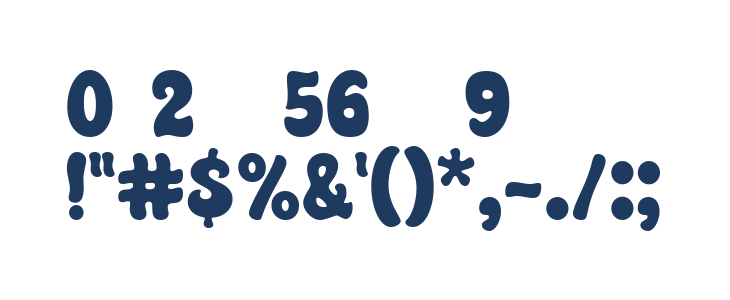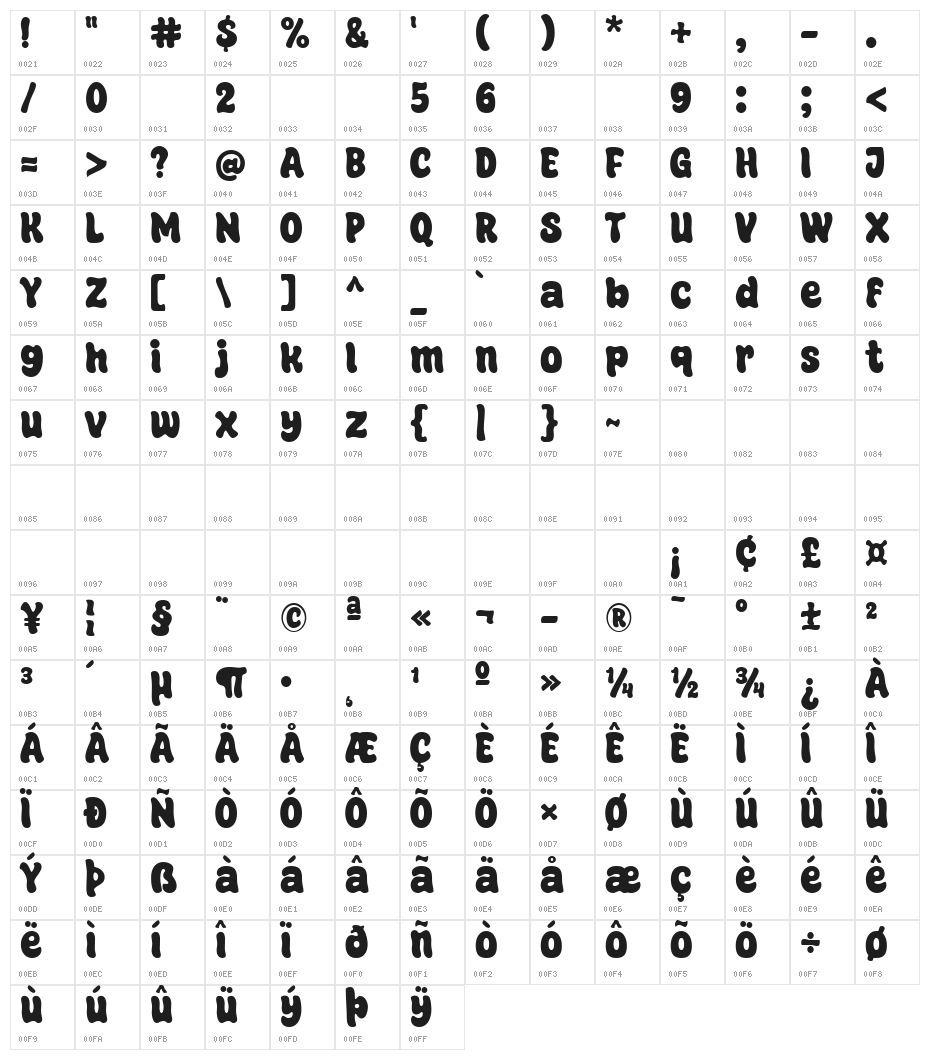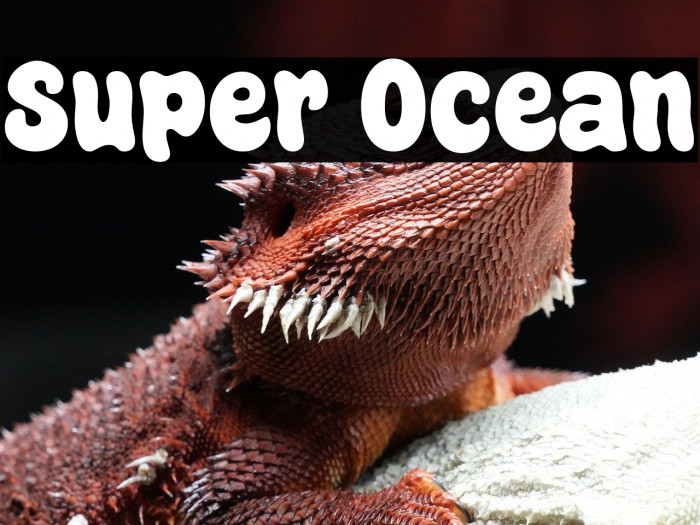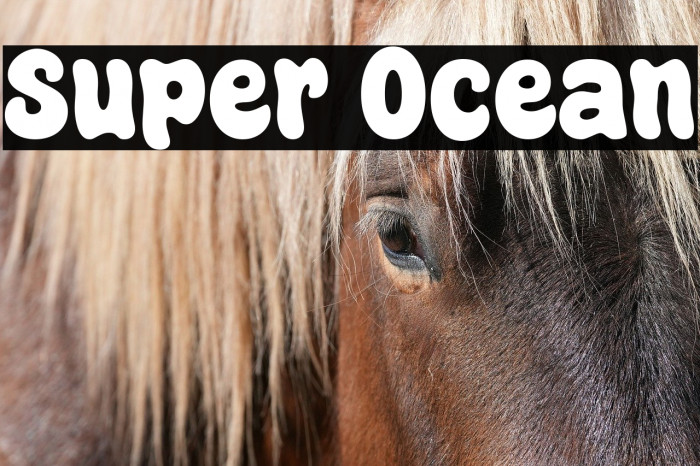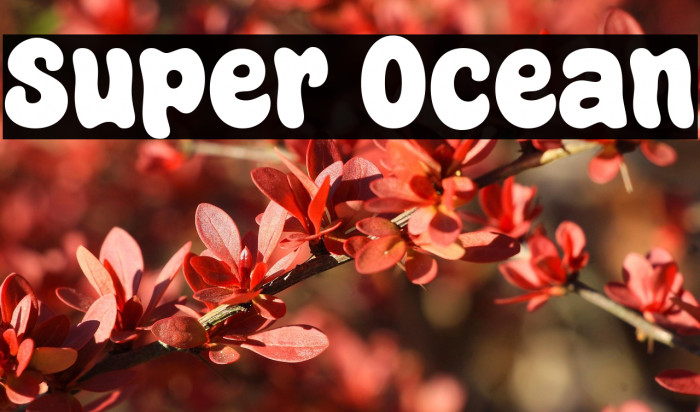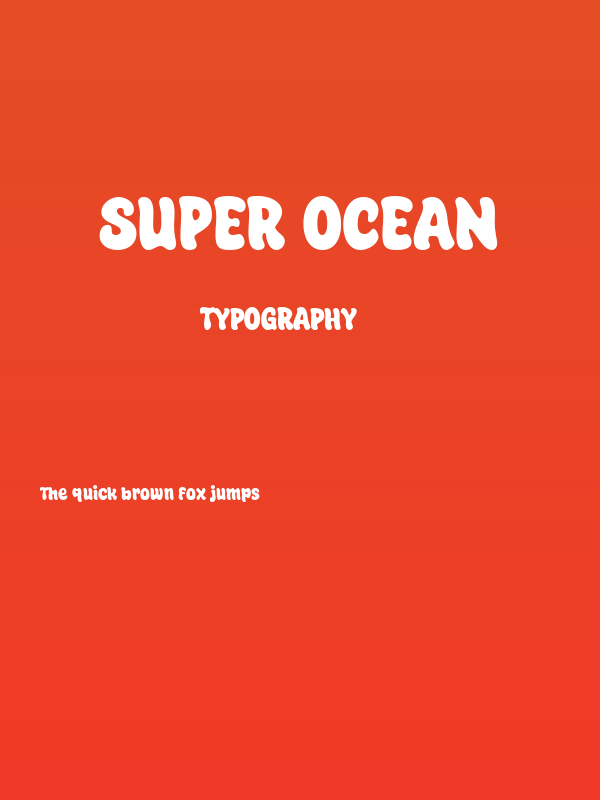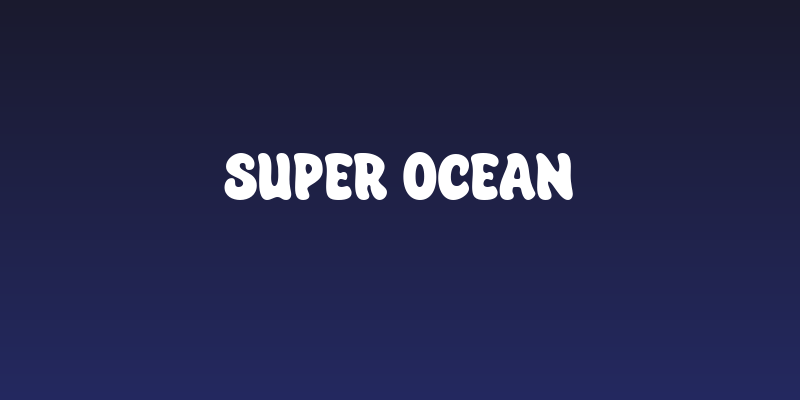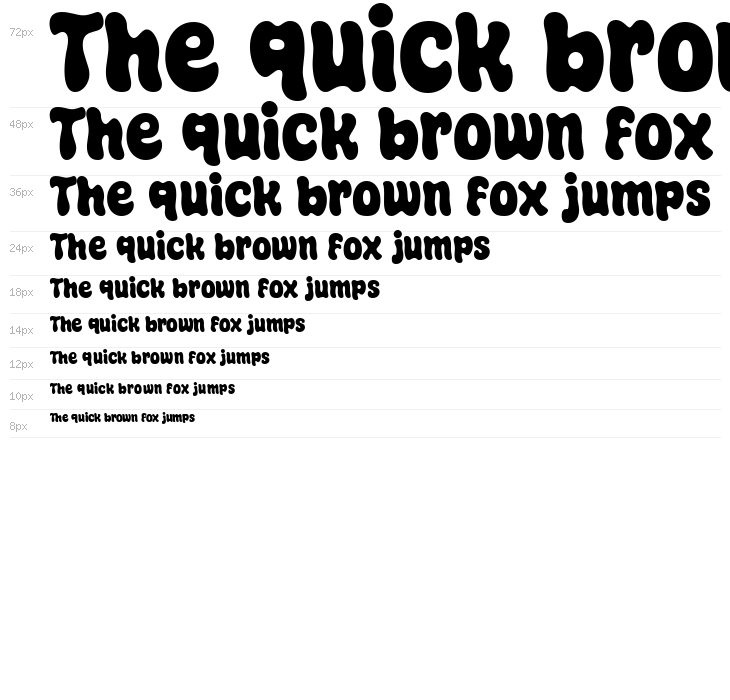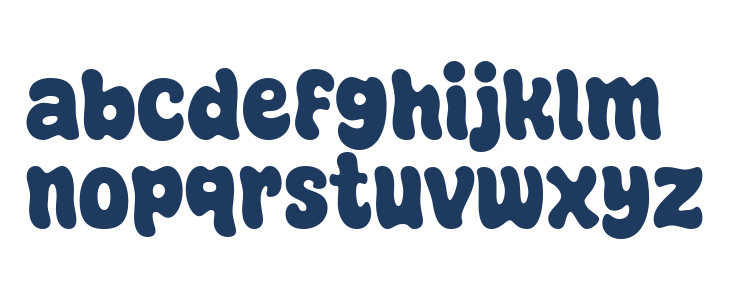
Super Ocean Font
| Stile generale | Playful, Whimsical |
| Progetti proposti | Ideal for children's books, playful branding, party invitations, and creative posters. |